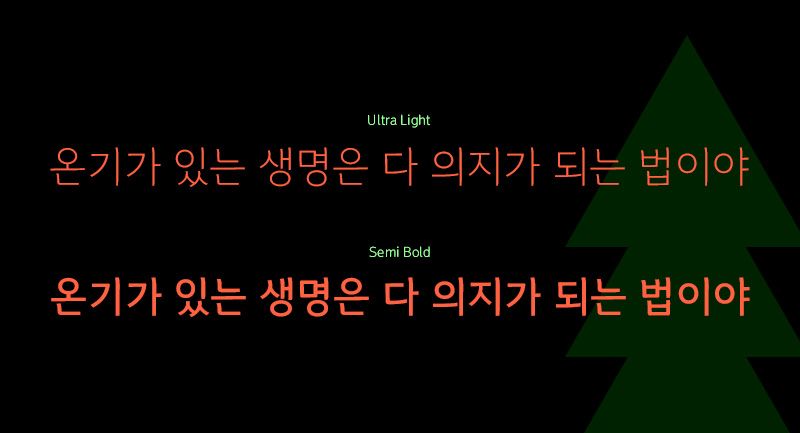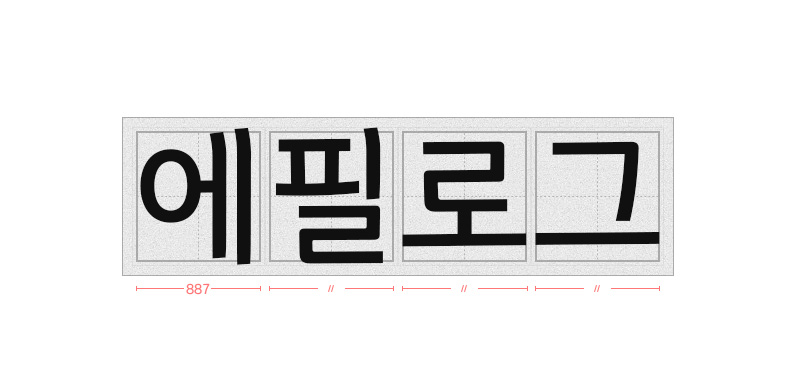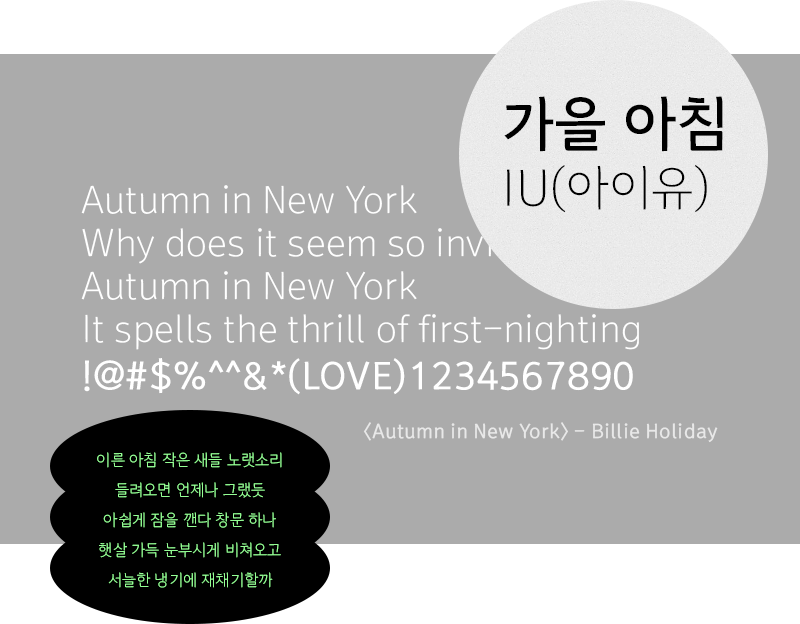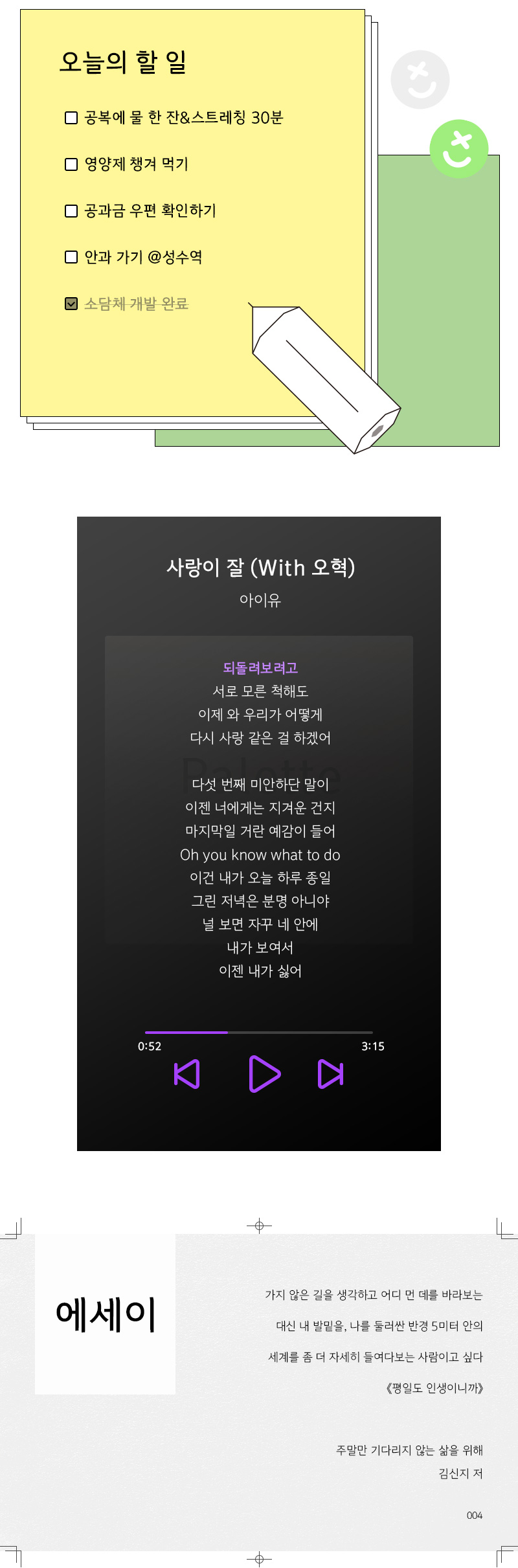
RixSodam
2 Style - Semi Bold, Ultra LightRix소담체는 이름처럼 깔끔하고 담백한 인상의 손글씨 서체입니다.
고딕 형태를 기본으로 자연스러운 꺾임과 곡선을 주어 따뜻하고 감성적인 느낌을 줍니다.
편안하고 담담한 분위기를 연출하여 본문과 제목 구분 없이 활용 가능합니다.
| FontFamily | Rix소담체 / RixSodam |
|---|---|
| Design | Park Yong-rak, Kim Geun-young, Lee Ji Yoon |
| Direction | Park Yong-rak |
- Semi Bold
- Ultra Light